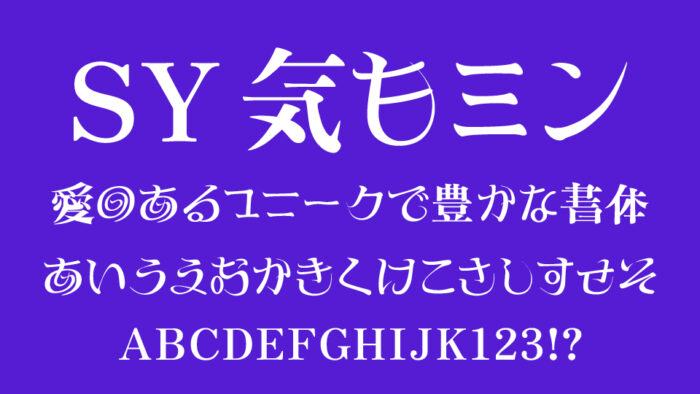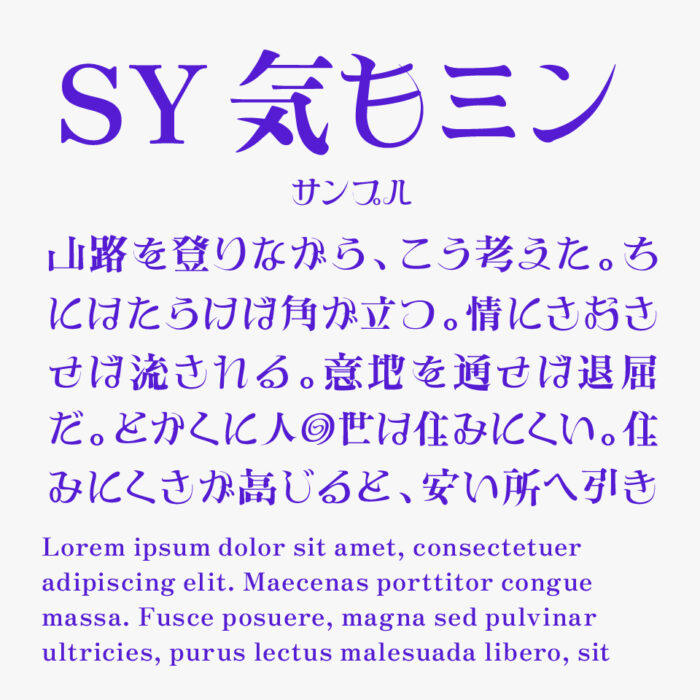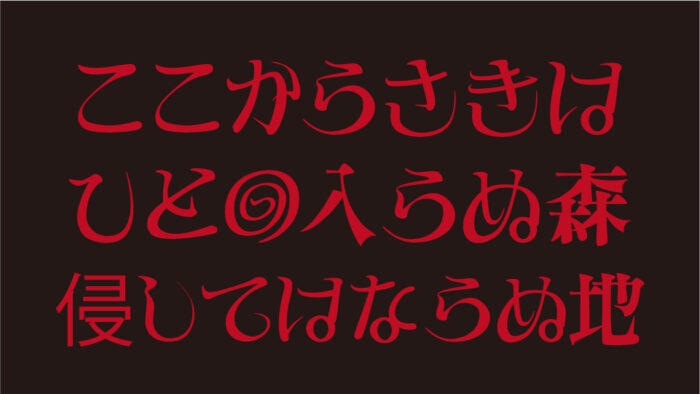
SY気もミンフォントは、文字の一部が歪んでいたり、崩れていたり、気味悪い雰囲気をもつ明朝体フォントです。
一部の文字が意図的に崩されていたり、形が歪んでいたりするのが特徴で、明朝体のスタイルをもち知的で文学的のように見えますが、どこか不穏で恐怖さを感じられてる不思議な明朝体フォントです。
SY気もミン
ホラーやミステリーなどのジャンルの雰囲気にぴったりデザインです。